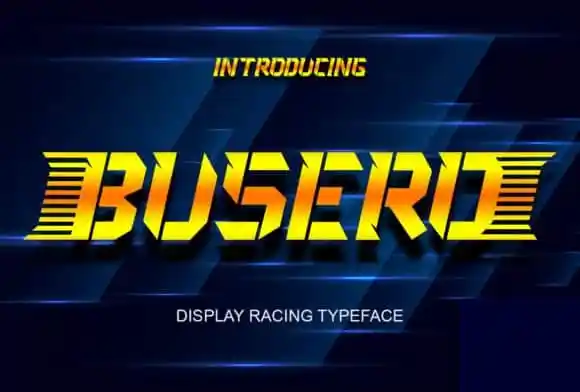
A Busero Display Font é uma elegante escolha para designers que procuram uma fonte forte e imponente. Seu estilo com cantos ásperos e linhas grossas, combinadas com um toque de intensidade e desenho bem executado, a torna fácil de identificar em qualquer projeto gráfico. Este é o tipo de fonte que Sealoung criou para trazer destaque às criações mais audaciosas e visionárias. Com um visual brilhante, a Busero Display Font se presta particularmente bem para aplicações visuais como jogos, aplicativos e filmes. Ela também é perfeita para títulos de animações e trailers, fazendo seus elementos destacarem-se em um meio cheio de desafios e tendências inovadoras. Com Busero, você pode explorar os limites do design e criar algo único que chame a atenção do público-alvo. Adicione esta fonte à sua próxima ideia criativa e veja como ela faz toda a diferença!